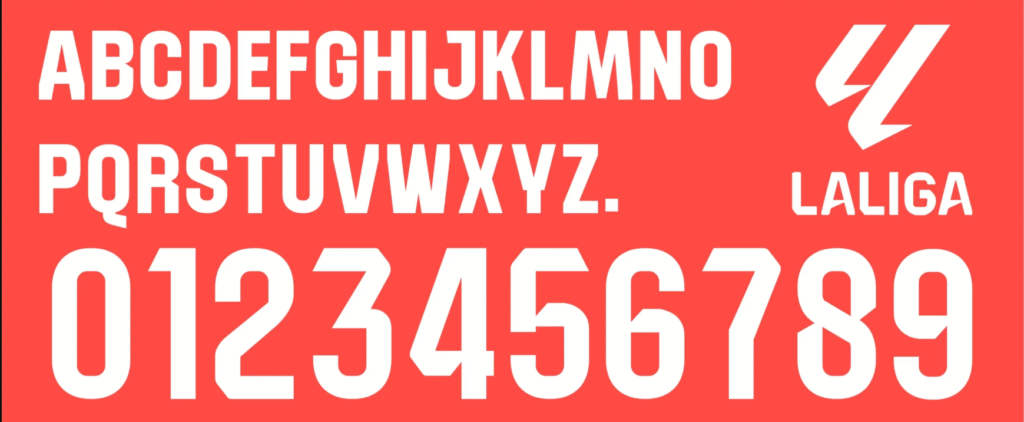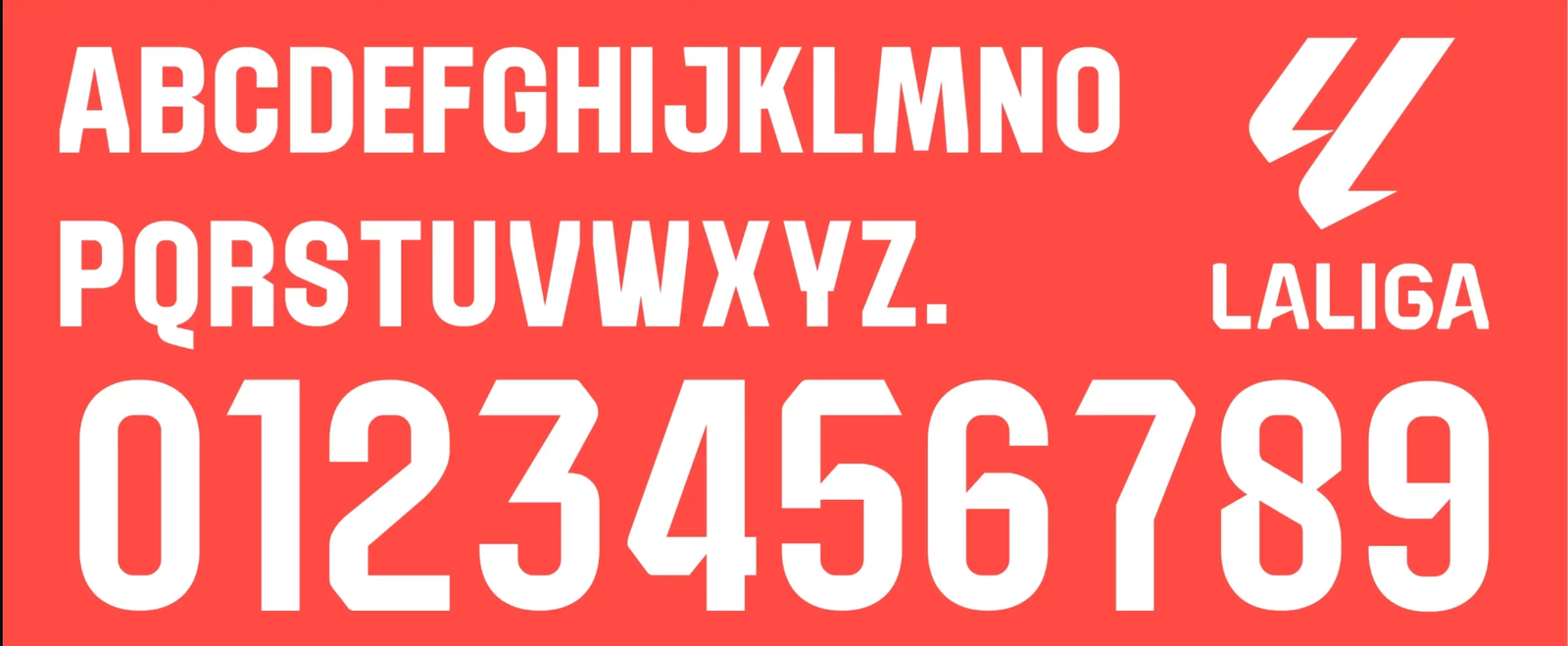
A La Liga é palco de algumas das maiores estrelas do futebol mundial e é referência em branding esportivo. Entre as temporadas 2017/18 e 2022/23, o campeonato espanhol implementou uma tipografia unificada obrigatória para a maioria dos clubes, visando fortalecer a identidade visual da competição nas transmissões globais.
Essa fonte histórica esteve presente nas costas das camisas de gigantes como Atlético de Madrid, Sevilla, Valencia, Real Betis e muitos outros durante os jogos da liga nacional. Se você busca fidelidade para recriar uniformes dessa “era de ouro” do futebol espanhol, este é o arquivo certo.
- Conteúdo: Alfabeto completo e numeração oficial com o logo da La Liga na base (em versões compatíveis).
Estilo Visual e Aplicação
A fonte padronizada da La Liga foi desenhada com foco total na legibilidade e na modernidade. Ela apresenta um estilo sans-serif condensado, com cortes angulares distintos e “rasgos” sutis nos números que conferem dinamismo e agressividade ao design.
É importante notar que, embora Real Madrid e Barcelona tenham utilizado fontes próprias em competições europeias (Champions League) ou em ações de marketing específicas, eles — e todos os outros times — foram obrigados a usar esta tipografia padronizada nos jogos do Campeonato Espanhol durante este período. Ela transmite uma sensação de unidade profissional e organização de alto nível.